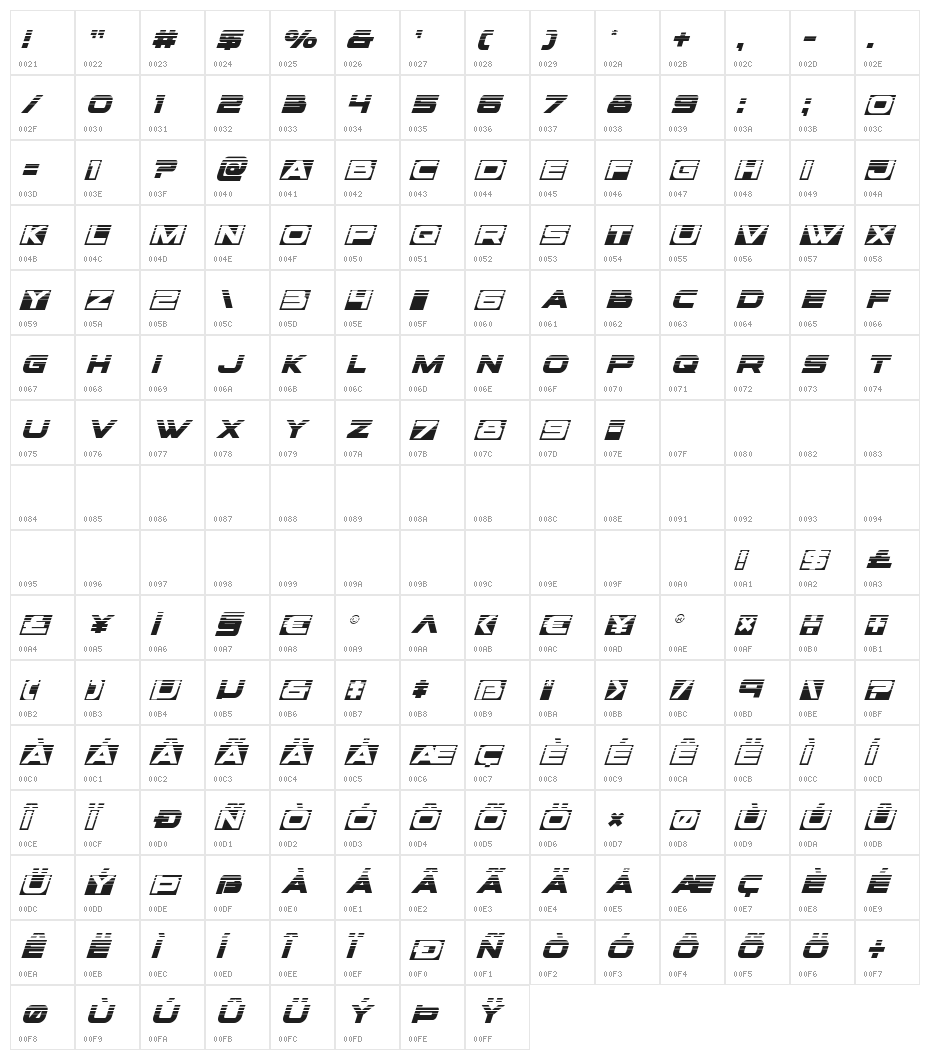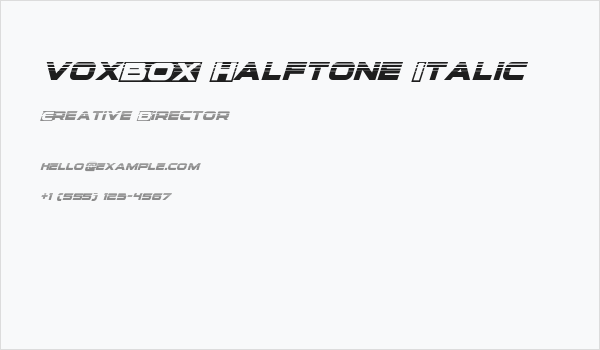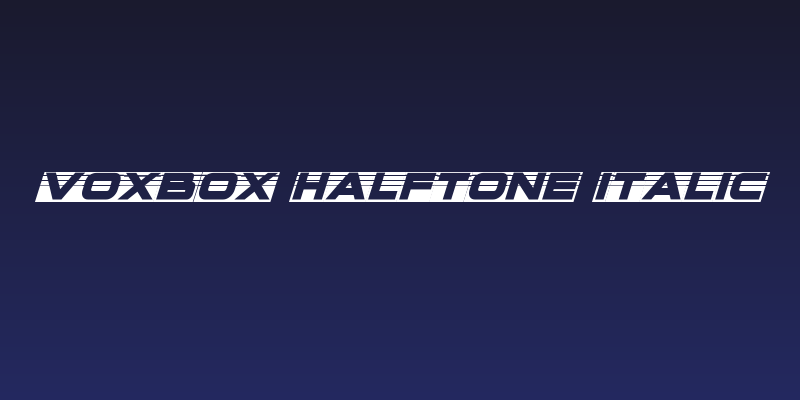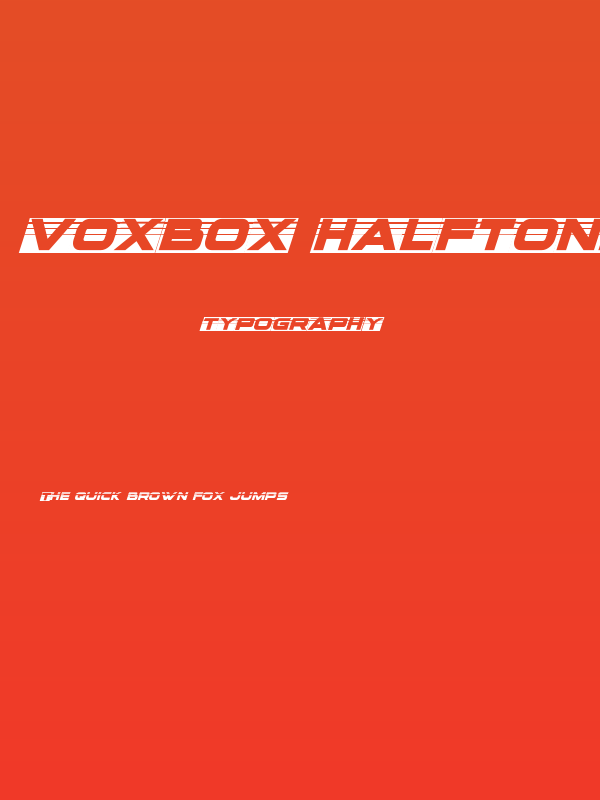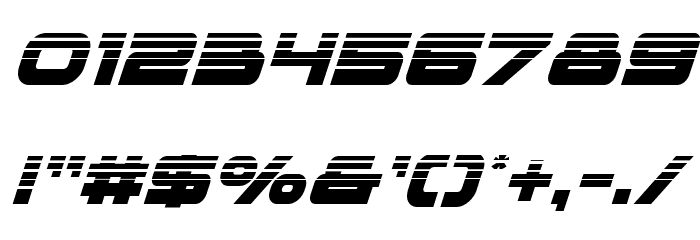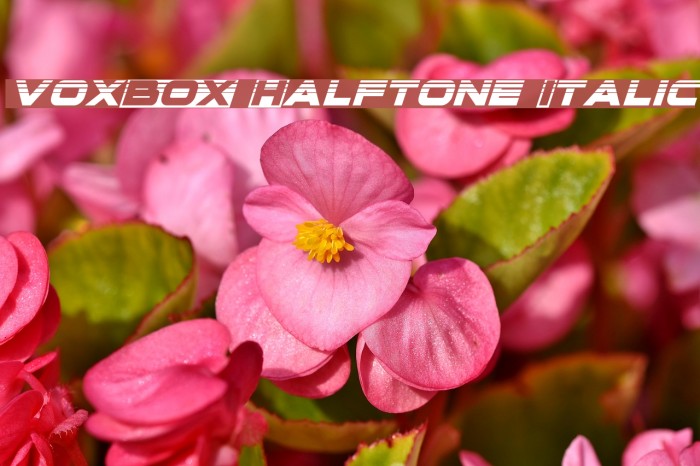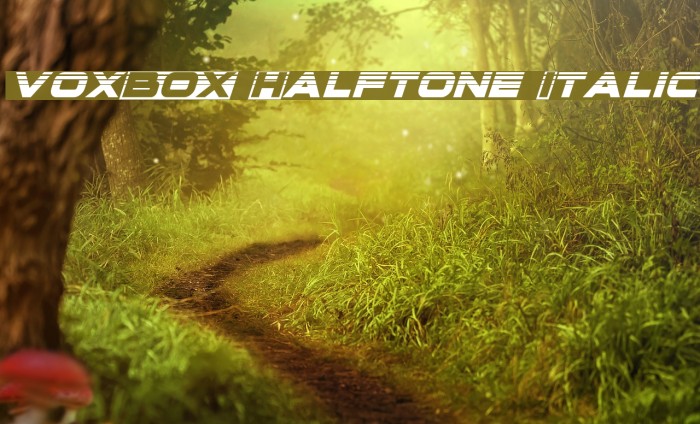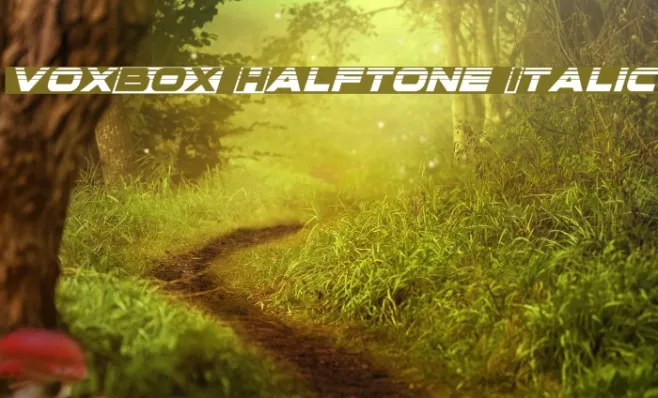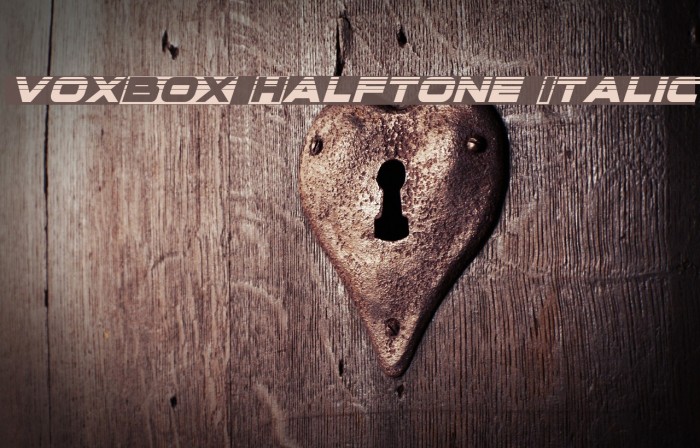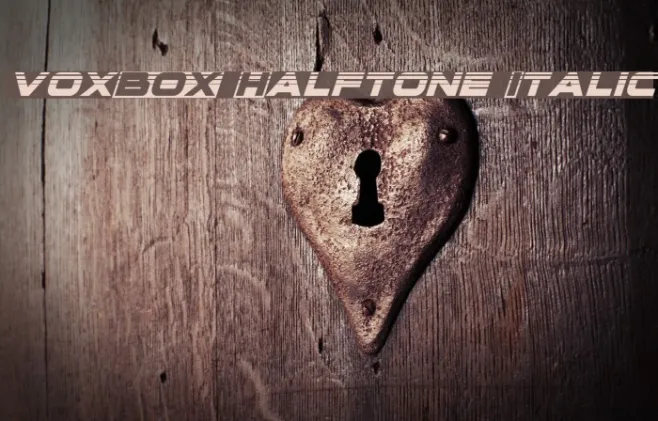
voxBOX Halftone Italic Font
| Estilo general | Futuristic, Dynamic |
| Proyectos propuestos | Perfect for use in sports branding, tech-related logos, or any project requiring a modern and energetic feel. |